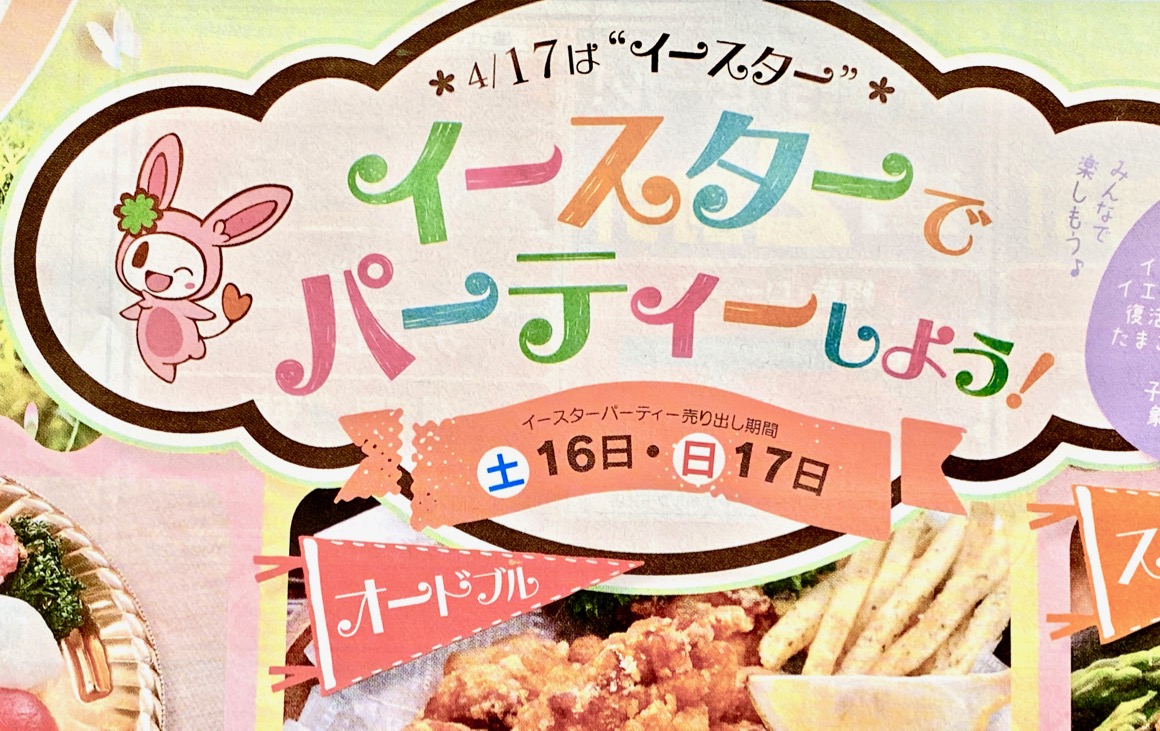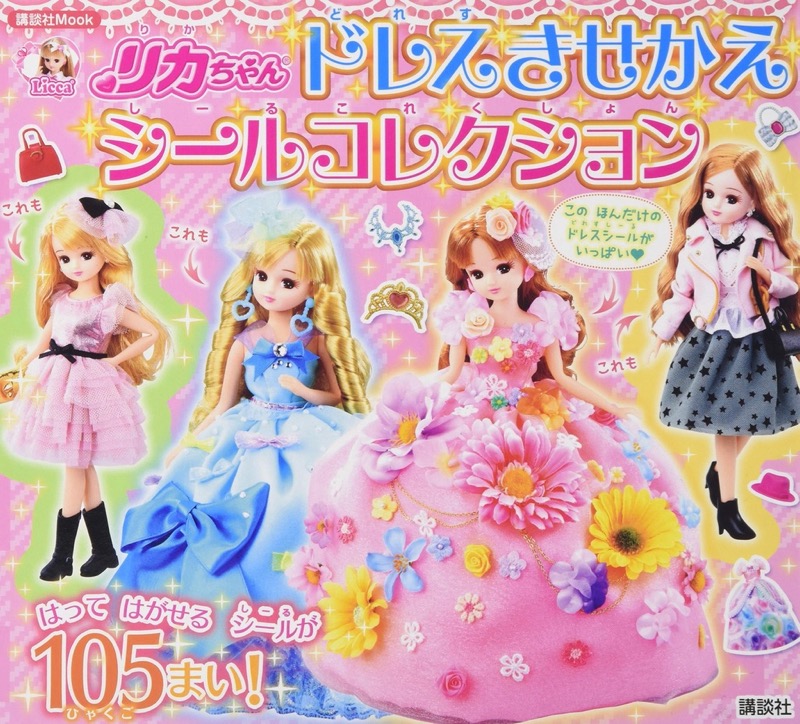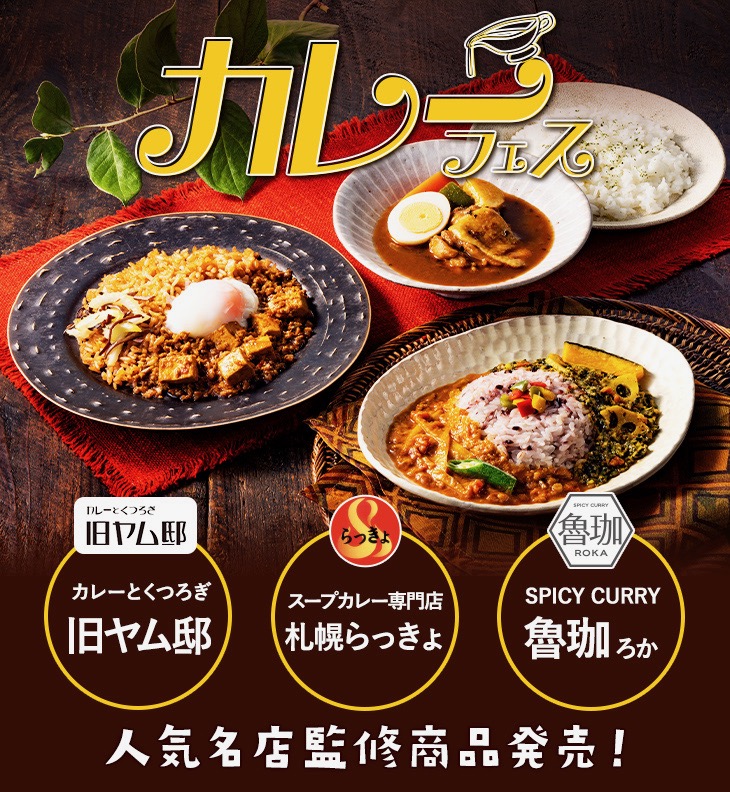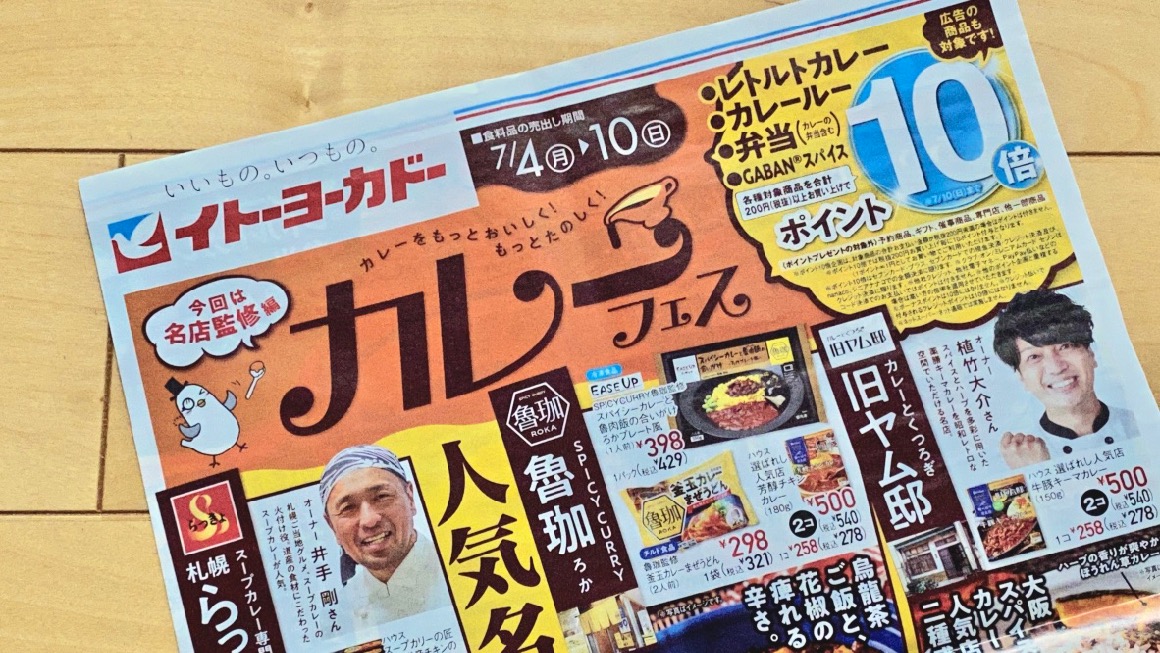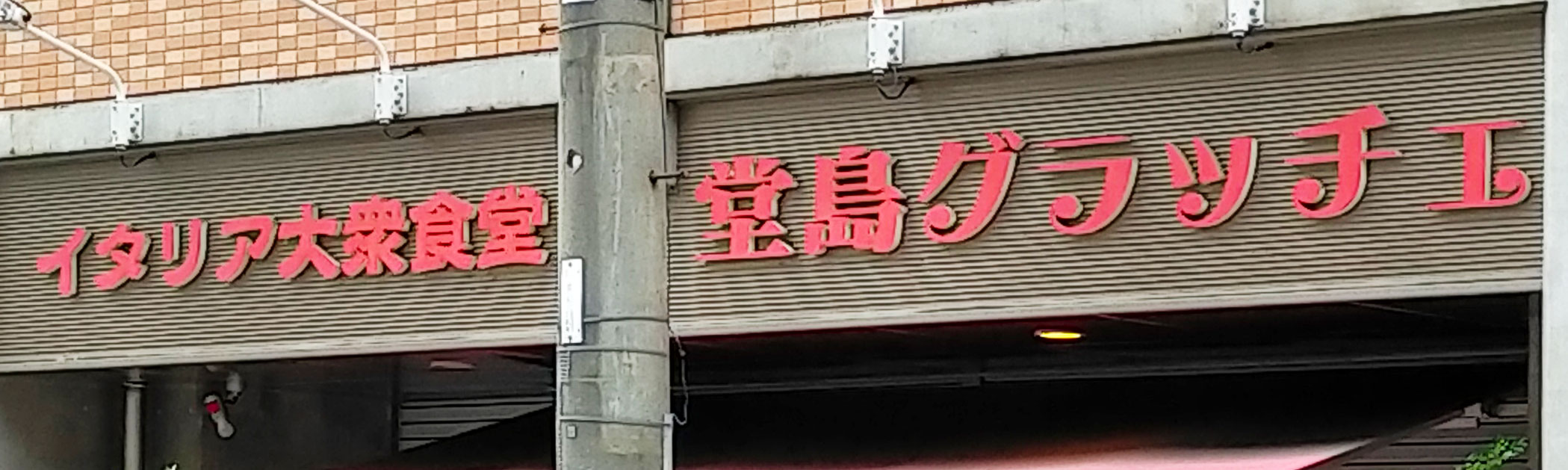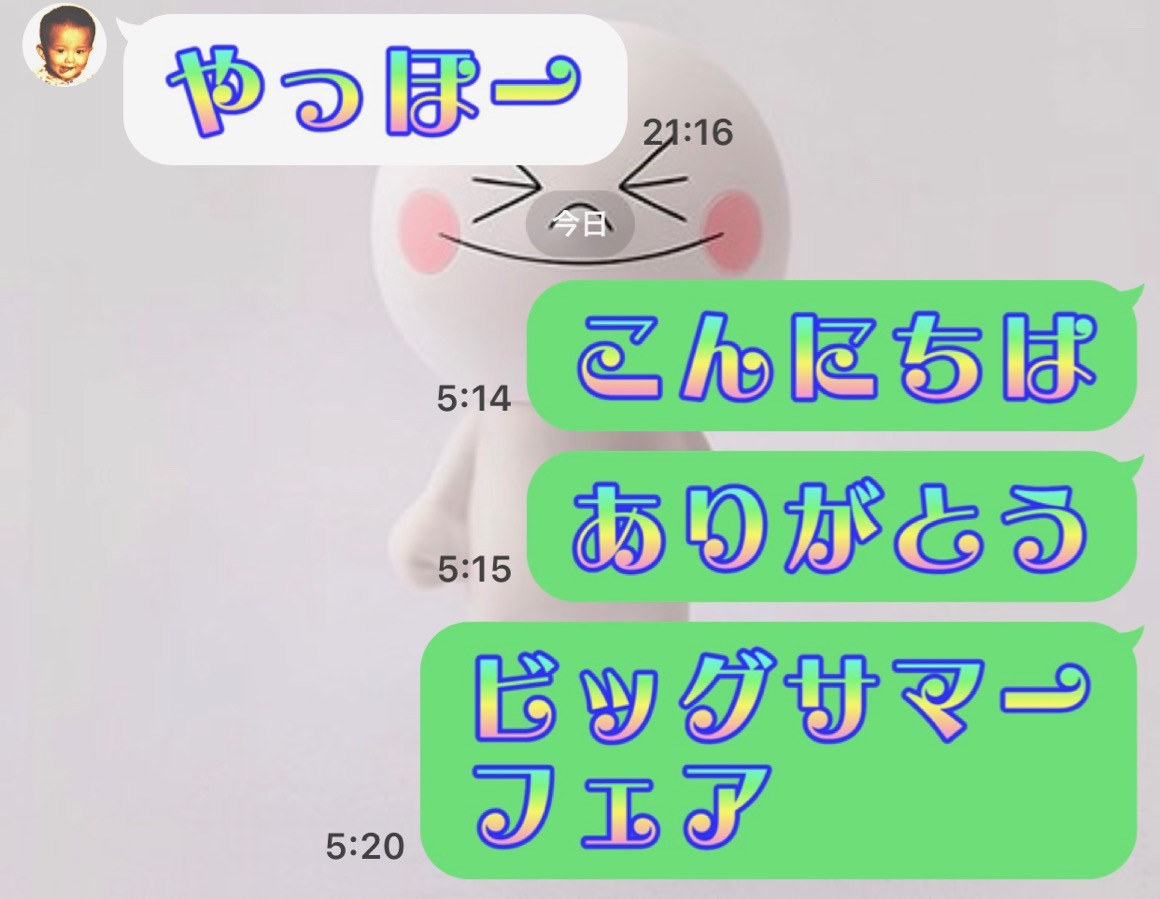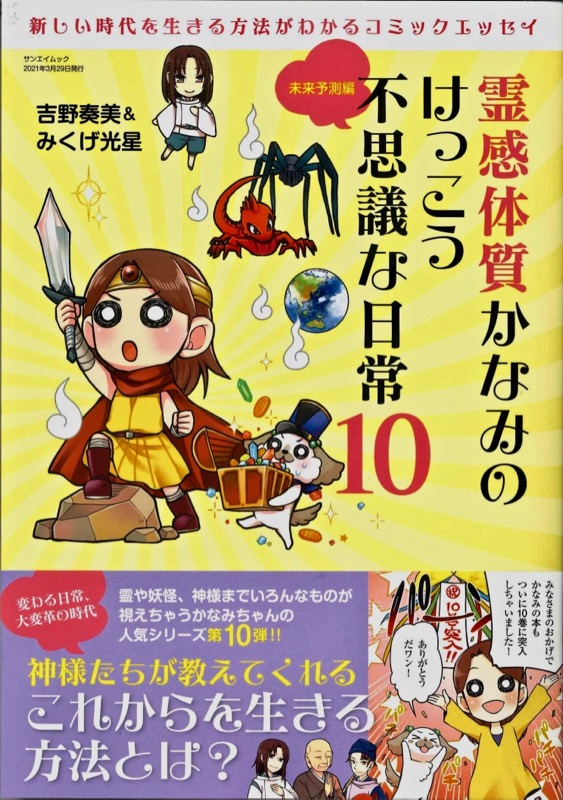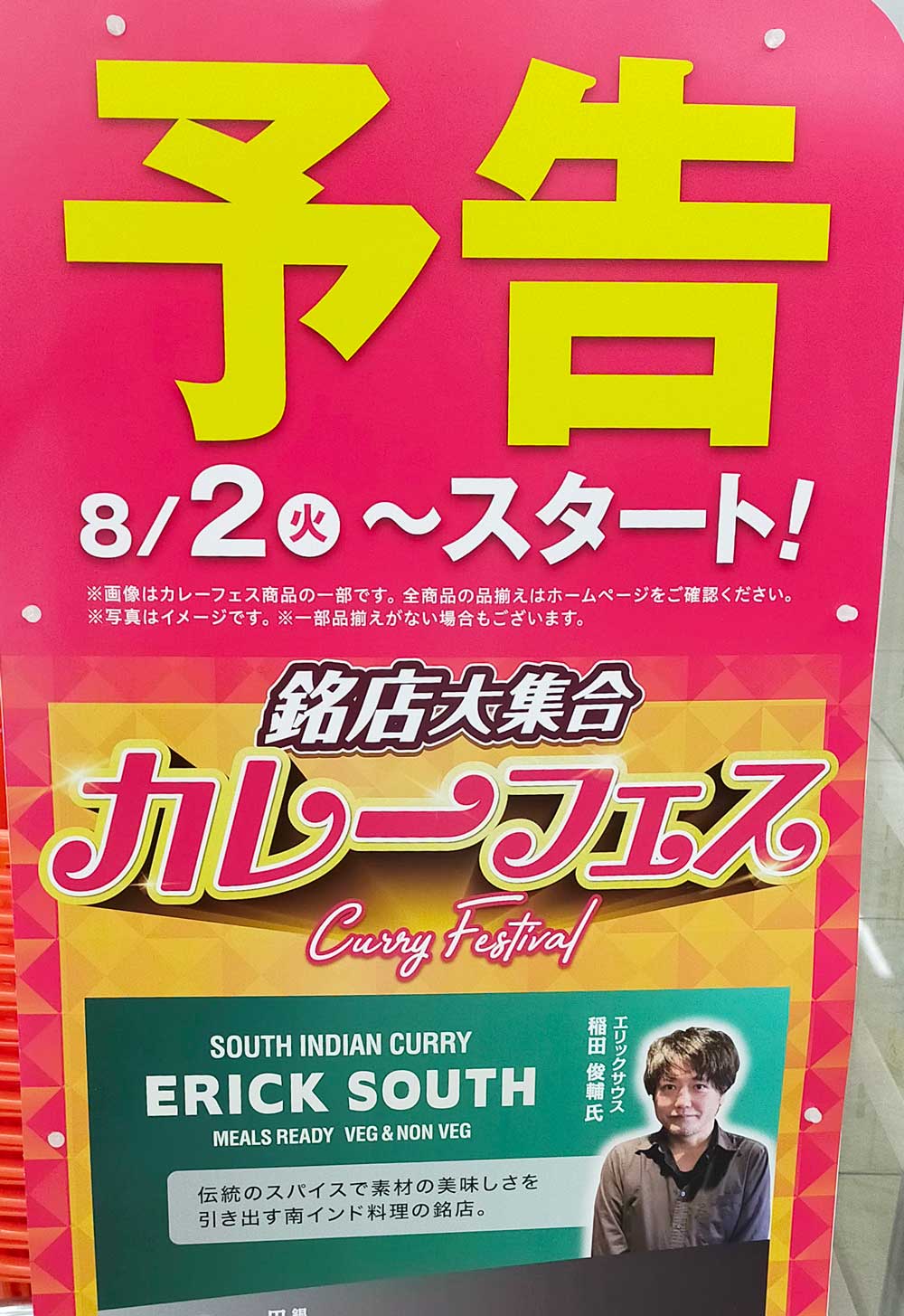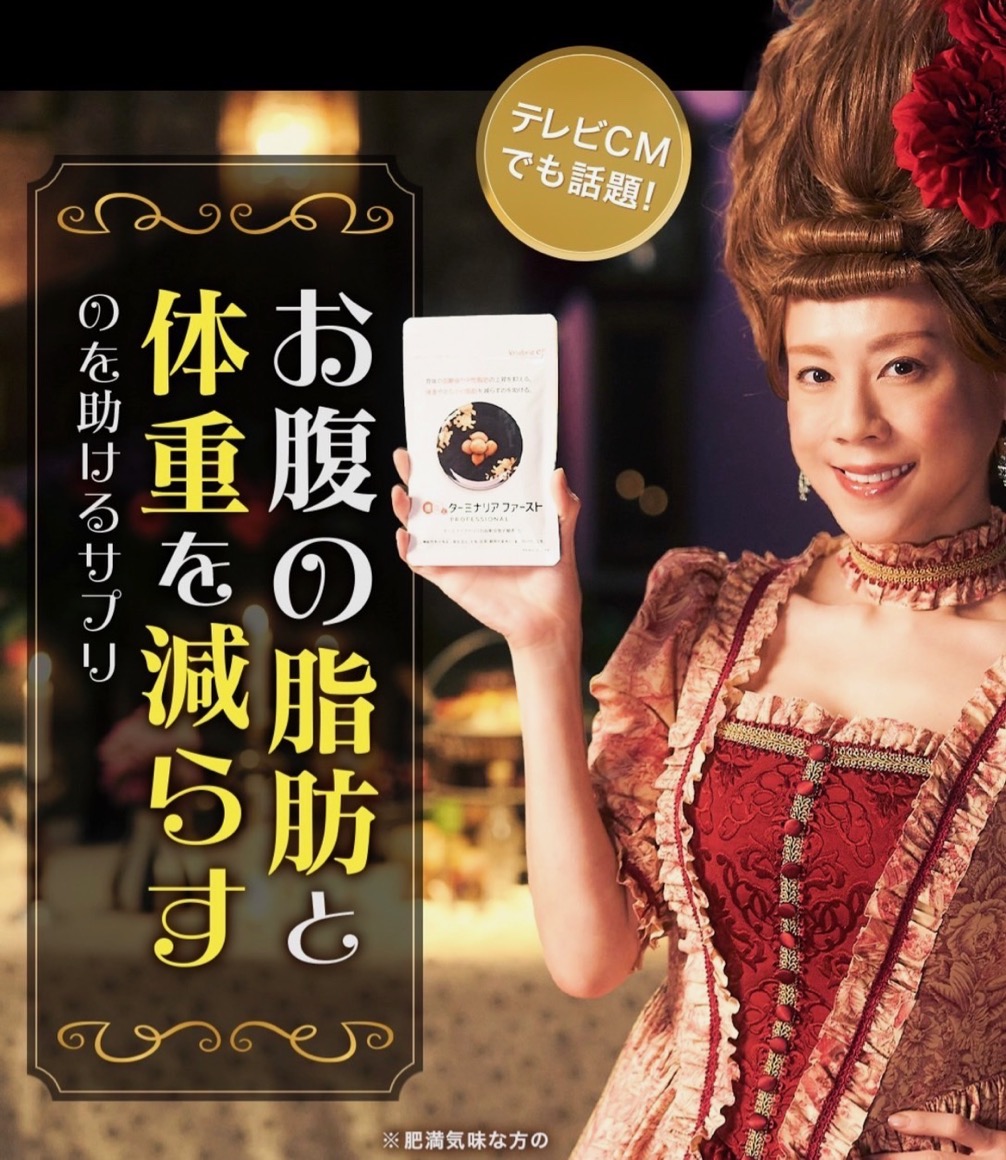
テレビ番組 さとうゆたか
NHKの「あさイチ」。
もうひとつ。
テレビ番組 さとうゆたか
フジテレビ「なりゆき街道旅」
コンサート さとうゆたか
Kenji Kaneko 2022.05 会津稽古堂 演奏会
これはポスターかな。
サムネイルに「えれがんと」が使用されています。
『運び屋』として危ない荷物を運ぶマインクラフト🚘💨【 マイクラ / Minecraft 】
日テレ「月曜から夜ふかし」 takumi
日本テレビで放送されている「月曜から夜ふかし」。
こういうキラキラした加工、「えれがんと」フォントのコンセプトやデザインとマッチしていますね。
こういう加工が似合う書体ですね。
貴族のチーズせん takumi
セブン-イレブンで見かけたお菓子のパッケージで「えれがんと」フォントが使われていました。
ほっかほっか亭の新メニュー takumi
ほっかほっか亭の新メニューだそうです。
「カリージャン」の文字がえれがんとだとすぐに判りますね。
「ー」はクルンとした加工が取られていますが…。
(違う書体を使ってる可能性も)
ほとんど同じですが、別パターンの画像をもう1枚。
この書体、なぜかカレーと相性が良いようですね。
イベントロゴ さとうゆたか
昨年のものだけど…。
海と日本プロジェクト「海・みなと・蒲郡」
広告画像 さとうゆたか
ネット上にときどき現れる転職広告。
テレビ番組 さとうゆたか
日本テレビの「笑ってコラえて!」。